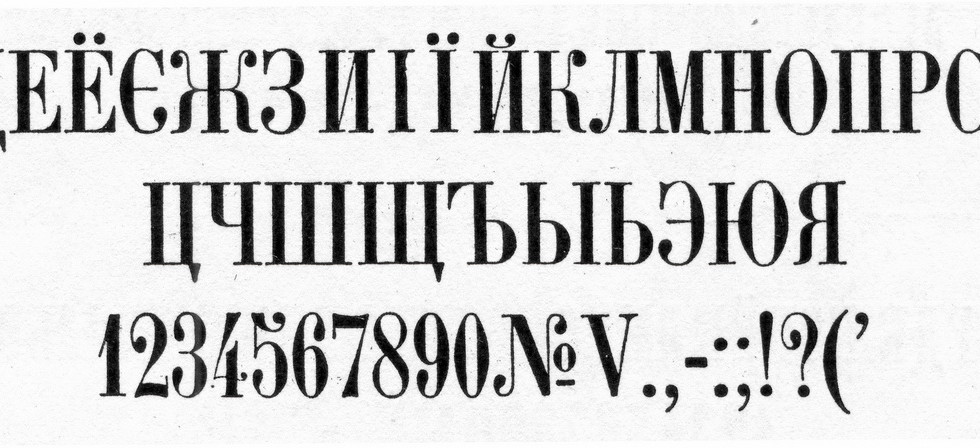
Шрифт Обыкновенный (типа Ревильон)/DXOldStandardRevilion
Выпущена цифровая версия шрифта Обыкновенный(типа Ревильон) Гарнитура №1. Образцами для воссоздания послужили оттиски шрифта из Каталога ручных шрифтов (Прапор, 1973 год) и Каталога ручных и машинных шрифтов (Издательство Книга, 1969 год). В составе гарнитуры два начертания: акцидентно-текстовое и декоративное оттененное.